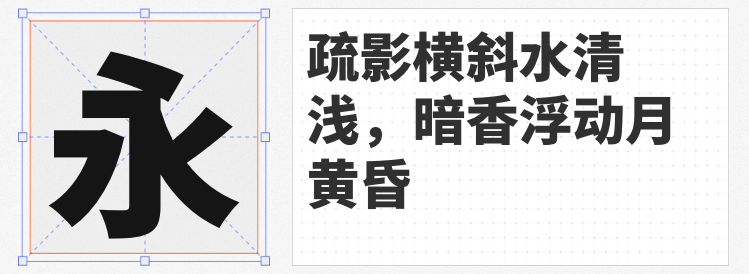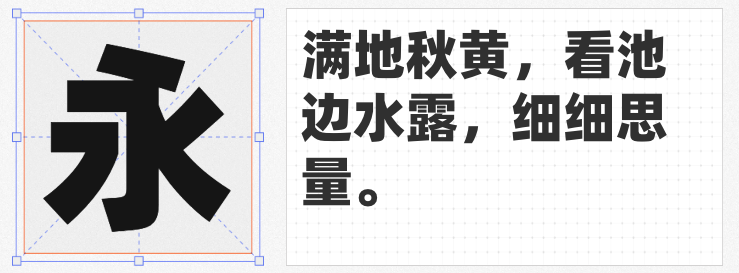
四款免费商用超粗黑体:设计中的力量美学之选
在视觉设计中,超粗黑体因其强烈的视觉冲击力和现代感,成为品牌传播、广告海报、数字界面等场景的“视觉锚点”。本文精选四款免费商用超粗黑体,从设计特征到应用场景,为设计师提供实用指南。
1. 思源黑体 SC Heavy
作为Adobe与Google联合开发的开源泛CJK字体,思源黑体自2014年发布以来便以“多语言支持”和“字重丰富”著称。其Heavy字重通过均匀的笔画粗细和几何化结构,传递出理性与秩序感,尤其适合科技、金融等行业的长文本排版或标题设计。得益于开源协议,设计师可自由修改并应用于商业项目,且支持简体中文、繁体中文、日文、韩文等多语言环境,是跨国品牌视觉统一的优选方案。
2. 锐字潮牌真言简2.0 超粗
锐字库推出的这款升级字体,以6款字重和可变字体技术突破传统限制。其超粗版本通过直角与圆角的错落搭配,在刚劲有力的笔触中融入婉转韵律,既保留黑体的现代感,又赋予字体独特个性。例如,在电竞、潮牌等年轻化场景中,其笔触的“曲折有度”与“落笔简洁”可强化品牌活力,而可变字体技术更支持设计师根据屏幕尺寸动态调整粗细,适配多元媒介。
3. 阿里巴巴普惠体 3 115 Black
阿里巴巴普惠体3.0版本新增生僻字库,覆盖古籍、地名等场景,其115 Black字重以瘦长字形和高重心设计展现“20岁少年的精气神”。笔画简化(如省略标题字出脚)与横竖粗细对比的弱化,使字体在超粗状态下仍保持轻盈感,避免视觉压迫。这一特性使其成为电商、快消品牌标题设计的利器,既能传递力量感,又符合年轻化审美趋势。
4. Aa厚底黑
Aa字库打造的这款字体,以窄长字形和大弧度曲线重构超粗黑体的视觉语言。其“厚底”设计通过加粗的笔画底部与流畅的弧线结合,营造出“稳重而不失灵动”的矛盾美感。在艺术展览、音乐节等场景中,其活泼感可打破传统黑体的严肃性,而窄长比例则适配移动端竖屏阅读,成为数字时代标题设计的“反套路”选择。
四款字体虽同属超粗黑体范畴,却通过不同的设计策略回应了多元场景需求,共同构建了超粗黑体的设计生态。设计师可根据品牌调性、媒介特性及受众偏好,灵活选用以实现视觉张力的最大化。